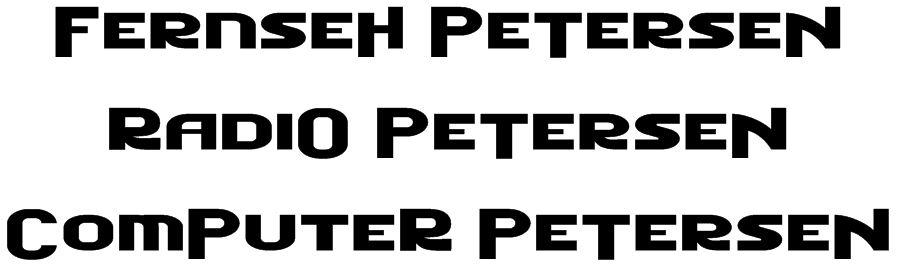
Suche Schriftart (Fernseh-Logo)
Ich suche die folgende Schriftart. Leider kann mir die Firma beim Schriftnamen nicht weiterhelfen.
Kann es sein, das dies eine Firma aus den Anfangstagen des Fernsehens ist, also dass man sich dort in den 1960ern schon die Glotze holen konnte?
Denn vergleiche ich hier die jeweils gleichen Buchstaben, sind die nicht 100% deckungsgleich, sodass ich hier einfach mal von Handarbeit eines Grafikers ausgehe.
ja die Firma ist schon recht alt. In zweiter Generation. Das wäre natürlich ärgerlich, wenn sich um einen selbst kreierten Schriftzug handel.
Wie sieht aus, wenn man sich die Buchstaben als Font erstellen lässt. Hat jemand Erfahrung damit? Kennt jemand einen zuverlässigen Anbieter? Was würde das für 8 Buchstaben ungefähr kosten?
Habs zwar noch nie gemacht, aber alternativ könnte ich die Buchstaben vielleicht auch selber erstellen. Hat damit jemand schon Erfahrung sammeln können? Gibt es dabei was zu beachten? Kennt vielleicht einer ein gutes Programm - was jetzt auch nicht zu viel kosten sollte.
In dem Zusammenhang: Gäbe es das Logo vielleicht in einer höheren Auflösung. Will man das nämlich hier nach bauen, muss man die Linienpositionen anhands der Pixeldichte raten. Das E hat beispielsweise gerade 18 Pixel in der Höhe.